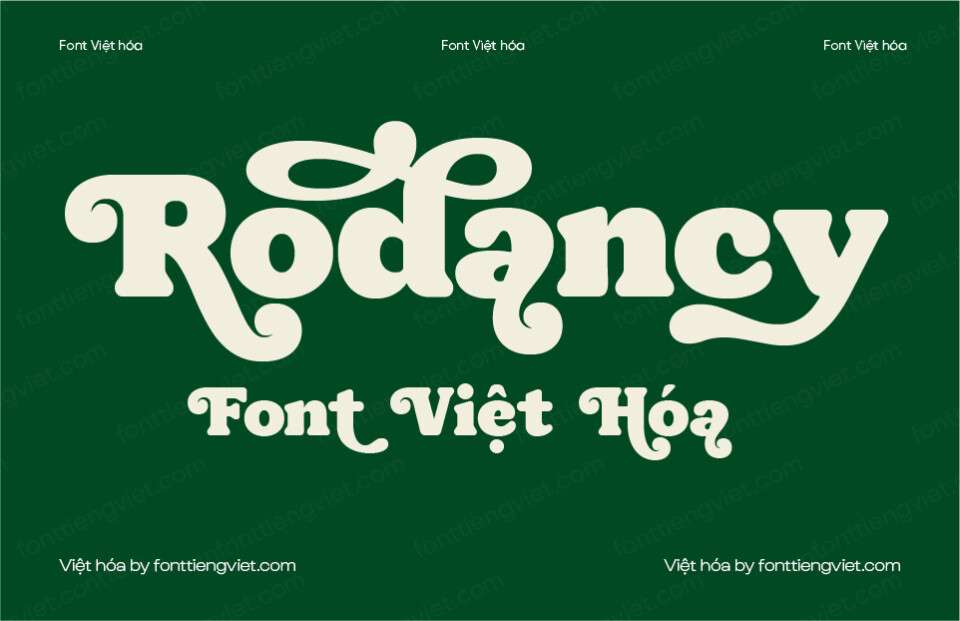
Trong thế giới thiết kế đồ họa hiện đại, việc lựa chọn một font chữ phù hợp có thể tạo nên sự khác biệt lớn cho tác phẩm của bạn. Đặc biệt, với những dự án yêu cầu tính thẩm mỹ cao và sự chuyên nghiệp, một bộ Font Chữ Việt hóa chất lượng là không thể thiếu. Hôm nay, chúng ta sẽ cùng đi sâu vào tìm hiểu về Font Việt hóa 1FTV VIP Rodancy – một lựa chọn tuyệt vời dành cho những ai đang tìm kiếm sự độc đáo, tinh tế và khả năng ứng dụng rộng rãi. Font này không chỉ đẹp mắt mà còn được tối ưu hoàn hảo cho tiếng Việt, giúp các bạn học sinh, sinh viên và cả những người làm thiết kế chuyên nghiệp dễ dàng tạo ra những ấn phẩm ấn tượng, từ bài thuyết trình học đường đến các ấn phẩm đồ họa phức tạp.
Tại Sao Font Việt Hóa 1FTV VIP Rodancy Lại Là Lựa Chọn Hàng Đầu?
Font Việt hóa 1FTV VIP Rodancy nổi bật giữa vô vàn các font chữ khác nhờ vào sự kết hợp hài hòa giữa tính nghệ thuật và khả năng đọc hiểu. Được thiết kế với những đường nét mềm mại nhưng vẫn giữ được sự mạnh mẽ, font Rodancy mang đến một vẻ ngoài rất riêng, khó có thể nhầm lẫn. Phiên bản Việt hóa 1FTV VIP đảm bảo rằng mọi ký tự tiếng Việt, từ dấu hỏi, dấu ngã đến các nguyên âm có dấu, đều được hiển thị một cách chuẩn xác và đẹp mắt nhất. Điều này cực kỳ quan trọng đối với các bạn học sinh khi làm bài tập, báo cáo hay thậm chí là bài thi tốt nghiệp, nơi sự rõ ràng và chuyên nghiệp của văn bản là yếu tố then chốt.
Không chỉ dừng lại ở mặt thẩm mỹ, font này còn được đánh giá cao về tính linh hoạt. Nó có thể dễ dàng thích nghi với nhiều loại hình thiết kế khác nhau, từ logo, branding, poster quảng cáo, đến thiết kế bìa sách, infographic và các ấn phẩm in ấn khác. Đối với các bạn sinh viên ngành thiết kế đồ họa, việc sở hữu một font chữ đa năng như Rodancy sẽ mở ra vô vàn cơ hội để thể hiện sự sáng tạo và nâng cao chất lượng các đồ án của mình.
Ưu Điểm Nổi Bật Của Font Rodancy Việt Hóa
-
Tính Thẩm Mỹ Cao: Với phong cách hiện đại và thanh lịch, Rodancy giúp các tác phẩm trở nên thu hút và chuyên nghiệp hơn.
-
Tối Ưu Hoàn Hảo Cho Tiếng Việt: Mọi ký tự tiếng Việt đều được chăm chút tỉ mỉ, đảm bảo không lỗi font, không bị vỡ chữ, mang lại trải nghiệm đọc mượt mà.
-
Đa Dạng Ứng Dụng: Phù hợp cho nhiều mục đích, từ thiết kế cá nhân đến các dự án thương mại, từ văn bản thông thường đến tiêu đề ấn tượng.
-
Ứng Dụng Của Font Việt Hóa 1FTV VIP Rodancy Trong Học Tập Và Công Việc
Đối với học sinh và sinh viên, việc trình bày đẹp mắt các bài thuyết trình, báo cáo khoa học hay đồ án môn học là rất quan trọng. Một bài thuyết trình với font chữ ấn tượng như Rodancy sẽ dễ dàng thu hút sự chú ý của giáo viên và tăng tính chuyên nghiệp cho nội dung. Đặc biệt, trong giai đoạn làm đồ án tốt nghiệp, nơi mỗi chi tiết nhỏ đều được đánh giá, Font Việt hóa 1FTV VIP Rodancy có thể giúp bản báo cáo của bạn trông nổi bật và được trình bày một cách chỉn chu nhất.
Không chỉ giới hạn trong môi trường học đường, font Rodancy Việt hóa còn là công cụ đắc lực cho những người làm trong lĩnh vực thiết kế và truyền thông. Từ việc tạo ra các ấn phẩm quảng cáo thu hút, thiết kế giao diện người dùng (UI/UX) thân thiện, đến việc phát triển bộ nhận diện thương hiệu độc đáo, font này đều có thể đáp ứng một cách xuất sắc. Sự rõ ràng và hiện đại của Rodancy giúp thông điệp được truyền tải một cách hiệu quả, đồng thời thể hiện sự chuyên nghiệp của người thiết kế.
Làm Thế Nào Để Tận Dụng Tối Đa Font Rodancy?
Để tận dụng tối đa tiềm năng của Font Việt hóa 1FTV VIP Rodancy, bạn nên cân nhắc một số mẹo sau:
-
Kết Hợp Hài Hòa: Dù Rodancy rất đẹp, việc kết hợp nó với các font chữ khác (ví dụ: một font sans-serif đơn giản cho phần nội dung) sẽ tạo ra sự cân bằng và dễ đọc hơn.
-
Chú Ý Đến Kích Thước Và Khoảng Cách: Đảm bảo kích thước chữ và khoảng cách dòng/chữ hợp lý để tránh gây mỏi mắt cho người đọc, đặc biệt là trong các tài liệu dài.
-
Màu Sắc Phù Hợp: Lựa chọn màu sắc tương phản tốt với nền để font Rodancy thực sự nổi bật và dễ đọc.
-
Thử Nghiệm Với Các Biến Thể: Nếu font có nhiều biến thể (regular, bold, italic), hãy thử nghiệm để tìm ra phong cách phù hợp nhất cho từng phần của thiết kế.
Tóm lại, Font Việt hóa 1FTV VIP Rodancy là một tài nguyên quý giá cho bất kỳ ai đang tìm kiếm một Font Chữ đẹp, chuyên nghiệp và tối ưu cho tiếng Việt. Với những ưu điểm vượt trội về mặt thẩm mỹ và khả năng ứng dụng, font này không chỉ giúp nâng cao chất lượng các sản phẩm thiết kế mà còn là công cụ hỗ trợ đắc lực cho các bạn học sinh, sinh viên trong quá trình học tập và làm đồ án. Đầu tư vào một font chữ chất lượng như Rodancy chính là đầu tư vào sự chuyên nghiệp và ấn tượng cho mỗi tác phẩm của bạn. Hãy khám phá và trải nghiệm sự khác biệt mà font này mang lại!